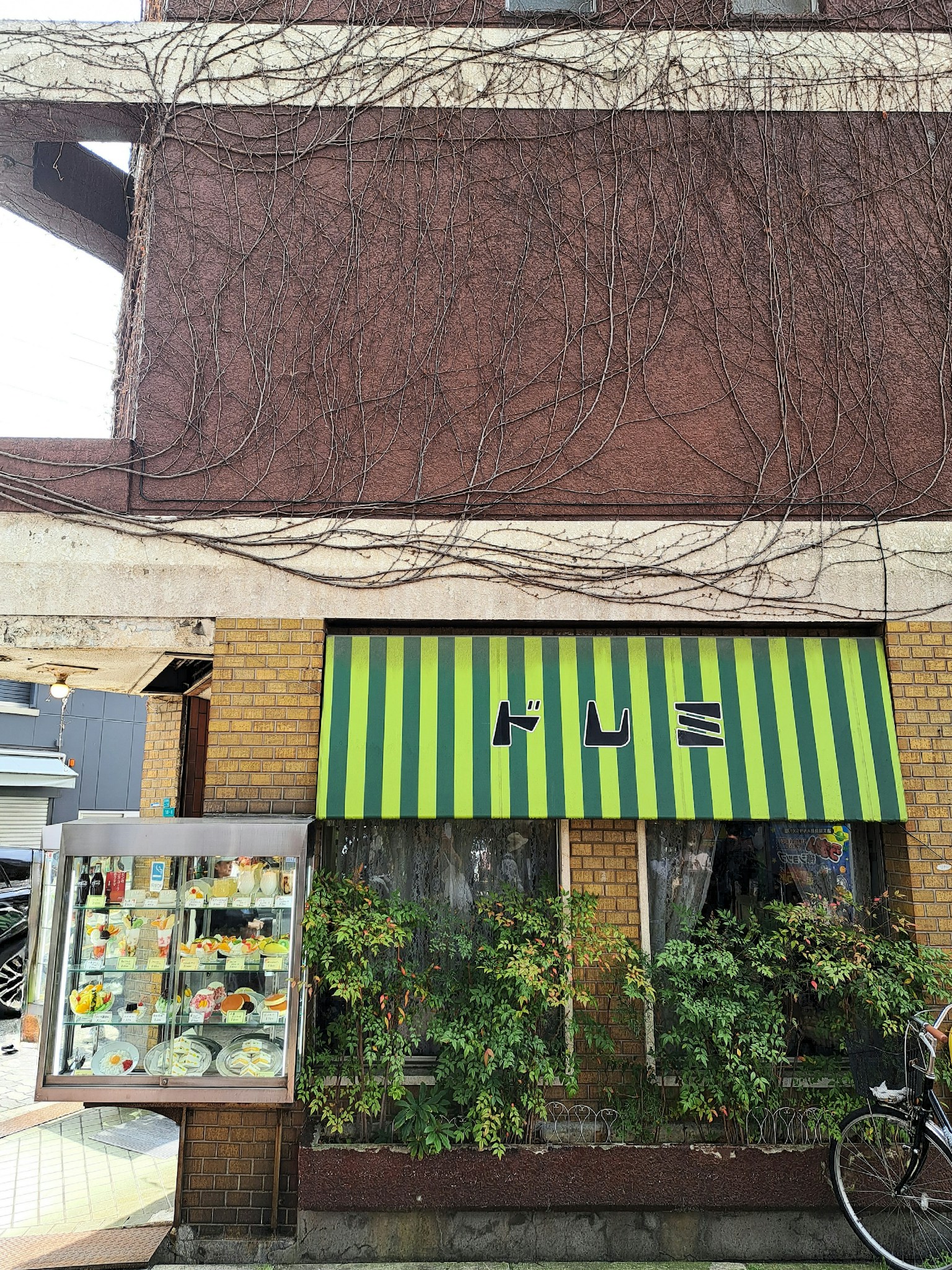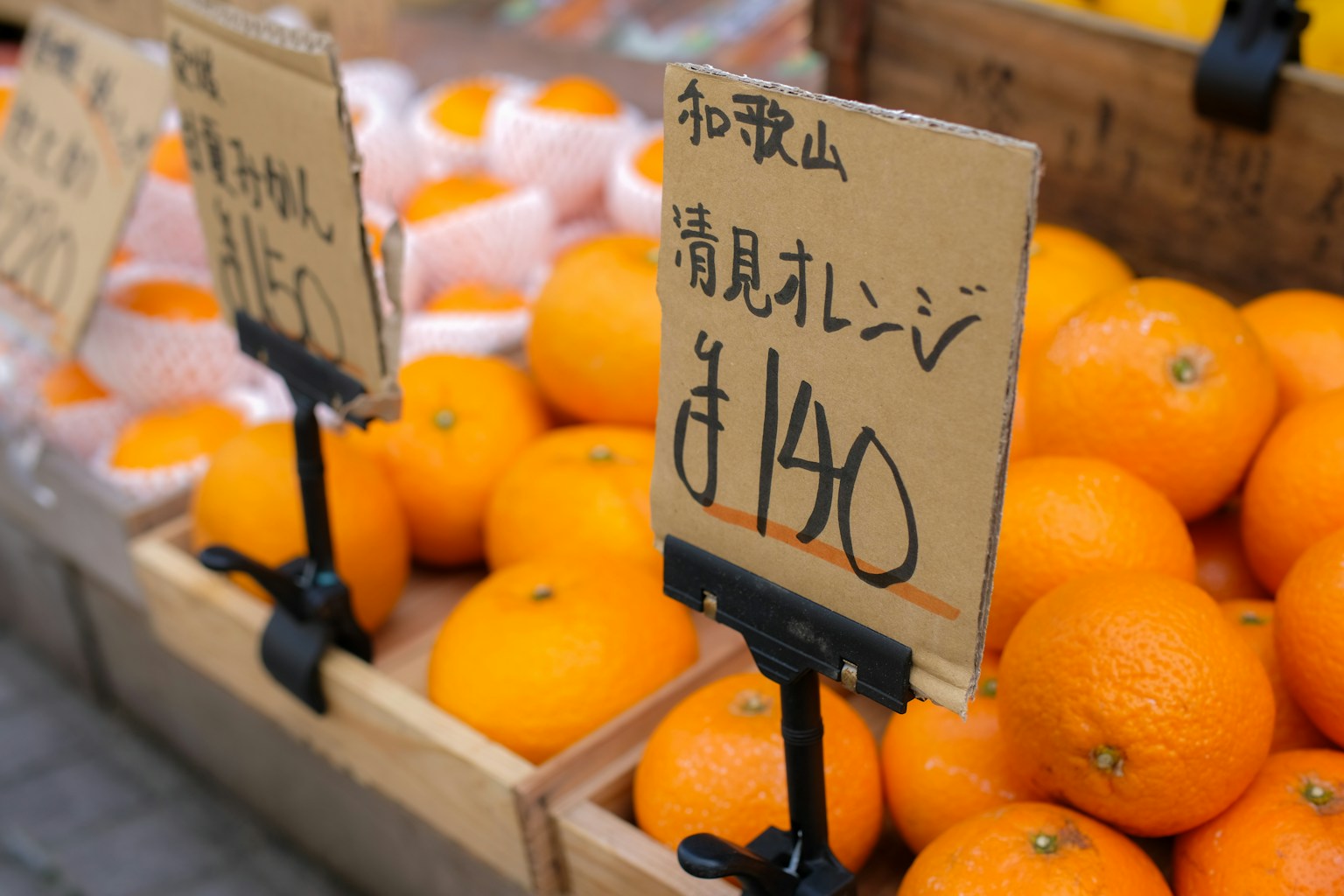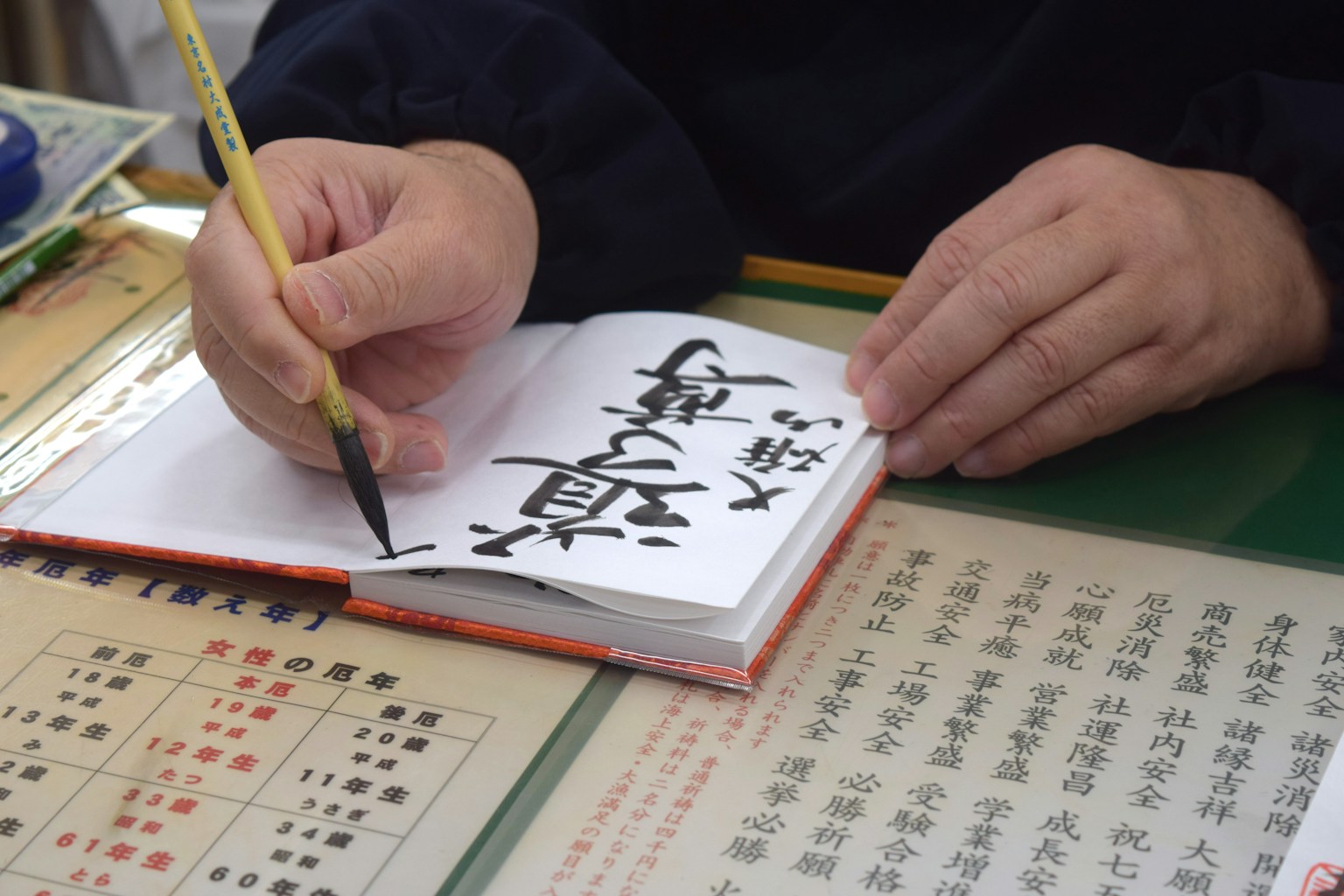
Indem Sie auf die Schriftarten der alltäglichen Texte achten, konnten Sie wahrscheinlich die Veränderungen in der Wirkung und Informationsübermittlung durch Schriften wahrnehmen.
In dieser Ausgabe präsentieren wir einige Werke, die im Rahmen der Hashtag-Kampagne gesammelt wurden.
Obwohl der Inhalt derselbe ist, verändert sich der Eindruck durch unterschiedliche Schriftarten erheblich. Wenn man darüber nachdenkt, sind Schriftarten doch faszinierend, oder?
Selbst stark abweichende Schriftarten, die weit von den in Lehrbüchern gelehrten schönen Schriften entfernt sind, können lesbar und sogar als charaktervolle Schriften wahrgenommen werden.
Auch die von Ihnen eingereichten Werke waren vielfältig und einzigartig, was die Hashtag-Kampagne zu einem großen Erfolg machte.
Nun möchten wir Ihnen einige der besonders bemerkenswerten Werke vorstellen!
Editor’s Choice #Font
Die auffällige Wassermelonenfarbe scheint nicht zur Atmosphäre zu passen, hat aber dennoch einen starken Eindruck hinterlassen. Die Schriftart selbst ist stark verzerrt und vermittelt nicht den Eindruck eines traditionellen Cafés.
Diese fehlende Einheitlichkeit trägt zum Gefühl eines altmodischen lokalen Cafés bei. Da der Name des Cafés 'Doremi' ist, fragt man sich, warum nicht ein schwarz-weiß gestreiftes Muster wie eine Klaviertastatur gewählt wurde.
Ein handgeschriebenes Preisschild auf einem Stück Pappe. Der Charme der Handschrift liegt darin, dass sie die Anwesenheit einer Person spüren lässt. In diesem Fall stellt man sich einen freundlichen Mann in Arbeitskleidung und Mütze vor. Auch die eigenwillige Darstellung des '¥'-Zeichens ist bemerkenswert!
Jedes einzelne Goshuin wird von Hand von einem Meister geschrieben. Die Schönheit der Kanji, mit ihren charakteristischen Strichen, wird durch den Pinsel hervorgehoben und steigert den Wert des Goshuin selbst. Da jedes Goshuin handgeschrieben ist, gibt es keine zwei identischen, was den Reiz des Goshuin-Sammelns ausmacht. Selbst wenn es die Schrift eines professionellen Kalligraphen ist, würde es gedruckt oder gestempelt seinen Reiz verlieren.
Zum Schluss
Wie fanden Sie es?
Beim Lesen von Texten ist die Schriftart ein ständiger Begleiter. Bei Namen von Geschäften oder Produkten kann sie auch das Branding beeinflussen. Umgekehrt kann eine geschickte Verwendung von Schriftarten einen positiven Eindruck hinterlassen. Es wird gesagt, dass es allein im Japanischen über 7000 Schriftarten gibt, und die Tiefe dieses Themas ist noch lange nicht ausgeschöpft.